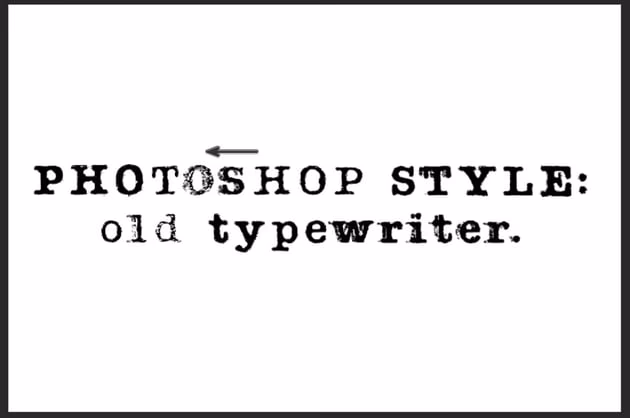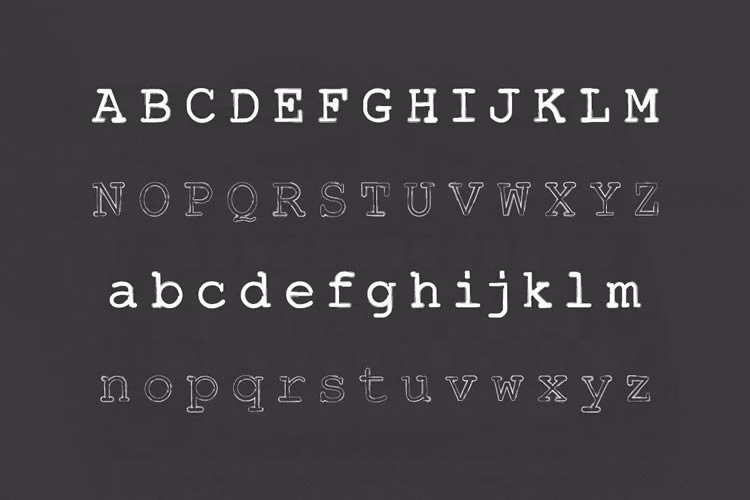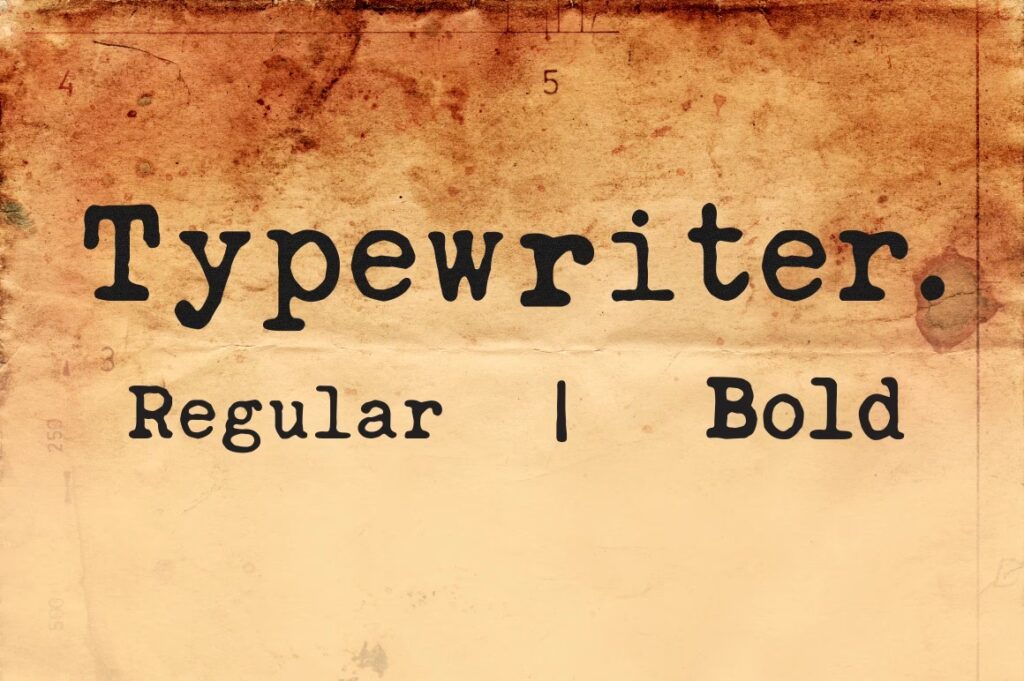
Skrivemaskineskrifttyper besidder en unik charme, der øjeblikkeligt fremkalder billeder af fortiden – fra vigtige dokumenter og litterære mesterværker til personlige breve og rå, autentiske notater. I dagens digitale verden har disse fonte fundet en ny plads i grafisk design, hvor de tilføjer karakter, tekstur og en følelse af håndværk, der ofte mangler i mere sterile, moderne skrifttyper.
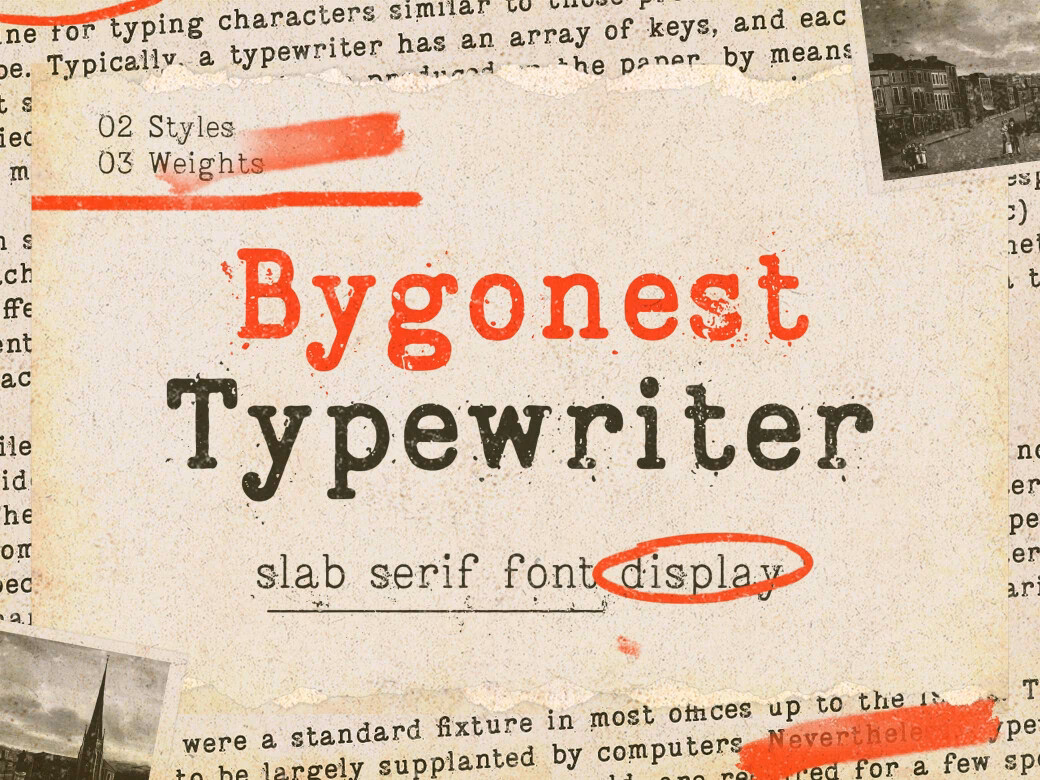
Når du arbejder med reklame- og salgsmateriale som brochurer og flyers for din virksomhed, eller skaber indhold til sociale medier eller websites, kan valget af den rigtige skrifttype have en enorm indflydelse på dit budskabs effekt. I stedet for at bruge store summer på at licensere nye, konventionelle fonte, kan skrivemaskinefonte – ofte tilgængelige gratis eller til en overkommelig pris – tilbyde en måde at skabe materiale, der føles unikt, friskt og skiller sig ud fra mængden.
Hvorfor Vælge en Skrivemaskinefont?
Skrivemaskinefonte er mere end bare bogstaver på en side; de bærer en historie og en æstetik, der kan berige ethvert design. De er perfekte til at tilføje et strejf af vintage eller en legende kant til dine projekter. Uanset om du ønsker et klassisk, tidløst look eller en mere grumset, slidt stil, findes der en skrivemaskinefont, der passer til formålet.
De visuelle karakteristika ved skrivemaskinefonte – som den monospaced afstand (hvor hvert tegn optager samme bredde), den let ujævne grundlinje eller effekten af blæk, der er løbet eller er forsvundet – bidrager til en følelse af ægthed og personlighed. Dette kan være særligt effektivt i design, der sigter mod at føles håndlavet, autentisk eller nostalisk.
Er Skrivemaskinefonte Tilgængelige i Moderne Designsoftware?
Selvom Adobe Photoshop eller andre designprogrammer måske ikke leveres med et kæmpe indbygget bibliotek af skrivemaskinefonte som standard, er det yderst nemt at tilføje nye fonte til disse programmer. Hundredvis, hvis ikke tusindvis, af skrivemaskinefonte er tilgængelige online – mange af dem gratis til personlig brug, og en god del også gratis til kommerciel brug. Andre kan købes fra typografiske biblioteker online.
Adobe Fonts-biblioteket, som er inkluderet i Adobe Creative Cloud-abonnementer, indeholder også fonte, der efterligner skrivemaskinens udseende. Den fulde Adobe Fonts-licens dækker typisk både personlig og kommerciel brug til designprojekter, webpublicering, PDF-indlejring og video/broadcast.
Hvilken Skrifttype Ligner Mest en Skrivemaskine?
Mens der findes et utal af kreative skrivemaskinefonte, er den mest kendte og generiske mulighed Courier eller Courier New. Denne skrifttype findes på de fleste tekstbehandlingsprogrammer og har den velkendte, retro serif-stil, som vi ofte forbinder med skrivemaskiner. Courier New blev specifikt designet til at efterligne stilen fra en skrivemaskine med en slab serif-stil og et monospaced design.
Men Courier er kun begyndelsen. Verdenen af skrivemaskinefonte er enorm og varieret, spændende fra pæne og rene til slidte og grumsede stilarter. Lad os udforske nogle af de mest bemærkelsesværdige skrivemaskinefonte, der er tilgængelige:
Et Udvalg af Populære Skrivemaskinefonte
Her er et kig på nogle af de bedste skrivemaskinefonte, der fremhæver den brede vifte af tilgængelige stilarter:
- Love Letter: Gratis til personlig brug. Denne font har en dejlig uperfekt effekt, der giver en rustik følelse og er perfekt til at tilføje et sentimentalt, menneskeligt præg. Den minder om tiden, hvor skrivemaskiner blev brugt til at udtrykke følelser.
- CarbonType: Helt gratis at bruge. Denne font er scannet direkte fra breve produceret af en Samsonite-skrivemaskine og giver et autentisk vintage-look, der er ubesværet cool. Fantastisk til plakater og projekter, der kræver kant.
- Thesis Typewriter: Kommer i tre stilarter (Weary, Regular, Bold). Den rammer en god balance og passer til mange forskellige projekter.
- Detective: Kombinerer gammeldags charme med moderne sensibilitet. En stemningsfuld og nostalgisk skrifttype, perfekt til projekter, der kræver et element af mystik. Bogstaverne er ikke helt ensartede, hvilket giver en autentisk og legende følelse.
- FF Trixie: Et alsidigt valg, hvis du søger en grumset skrivemaskinefølelse. Trixie-familien har 12 forskellige variationer og passer til et bredt spektrum af projekter. Den har en rig historie, der går tilbage til 1930'erne.
- Letter Gothic: Designet for IBM i starten af 60'erne. Dette er en af de renere skrivemaskinestile med flade, monospaced sans-serif bogstaver. Ren og smuk, tilgængelig i forskellige vægte. Ikke fokuseret på det slidte look, men mere på en ren, teknisk skrivemaskine-æstetik.
- Scripter Serif: En anden ren skrivemaskinefont, men med seriffer. Meget læselig, hvilket gør den velegnet til logo- og brandingarbejde. De rene linjer får den til at føles mere moderne, hvilket giver en tidløs elegance snarere end et strengt vintage-look.
- Olivetti Typewriter: God til at efterligne den sjuskede blæk-effekt fra ældre maskiner. Skabt af designer Iza W., tilgængelig i fem forskellige vægte og en god mulighed for en traditionel skrivemaskinestil.